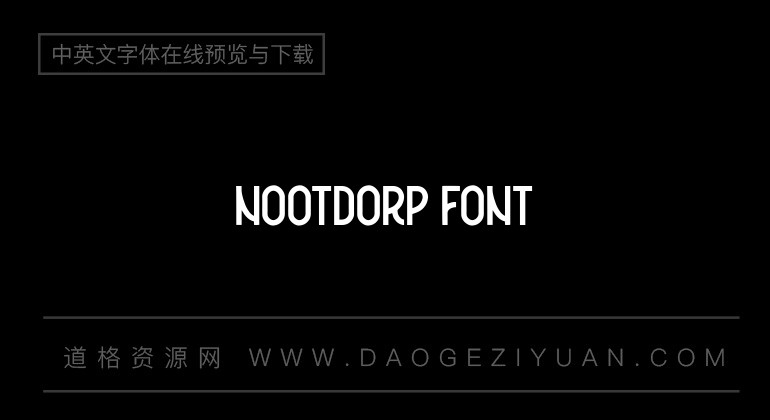
Nootdorp Font
Nootdorp Font 是一种现代化的无衬线字体,与许多其他无衬线字体一样,它的设计风格注重简单、直接和易读。 Nootdorp Font 字体的特点之一是它的字母具有几何形状,这使得它在视觉上更加整洁和现代化。同时,该字体的字母间距、字母高度和字母宽度都非常均匀,这也有助于提高其可读性和美观度。 Nootdorp Font 字体包括多种字重和字型,可用于设计各种印刷品和数字媒体。该字体适用于多种场合,如标题、标志、海报、网站和移动应用程序等。
Nootdorp Font是一款非常不错的手写艺术字体,具有很好的视觉感,适合于文化类的宣传设计、商业类品牌的广告和产品包装设计以及个性化文字排版等较多场景。